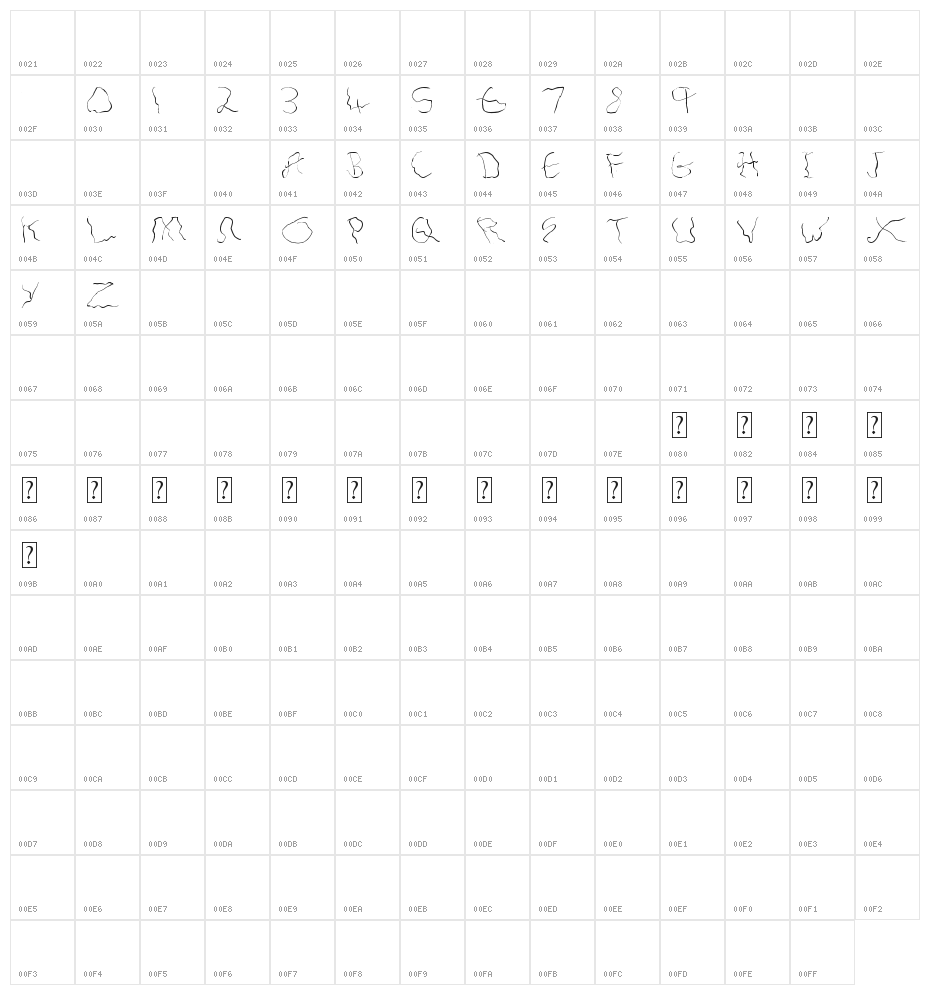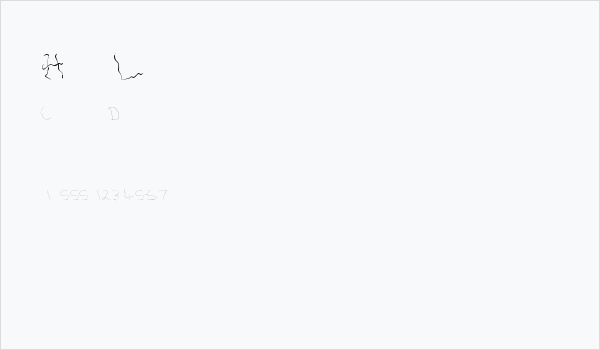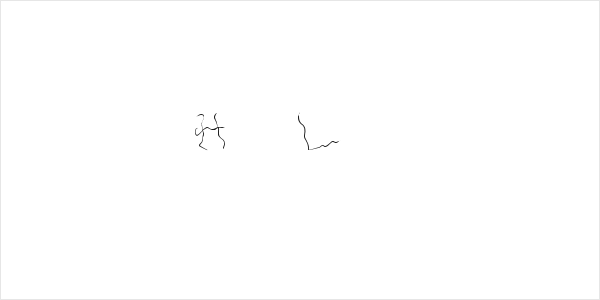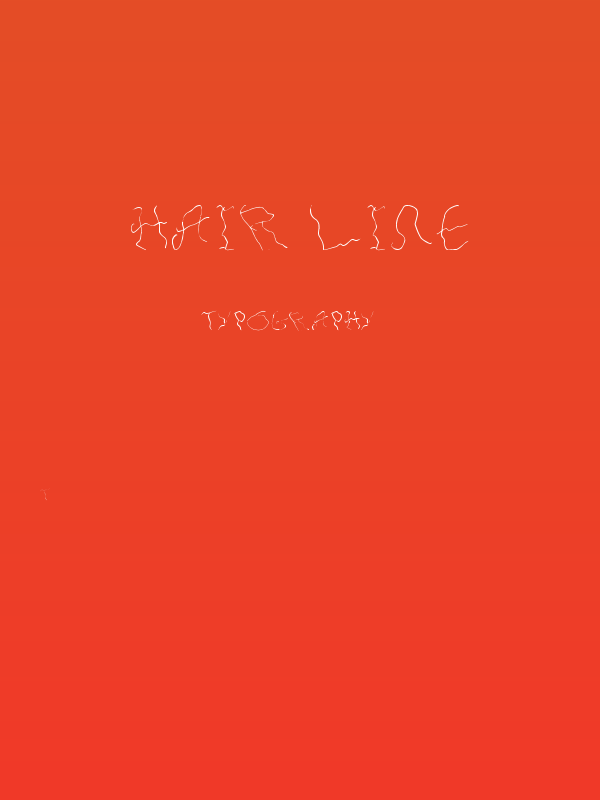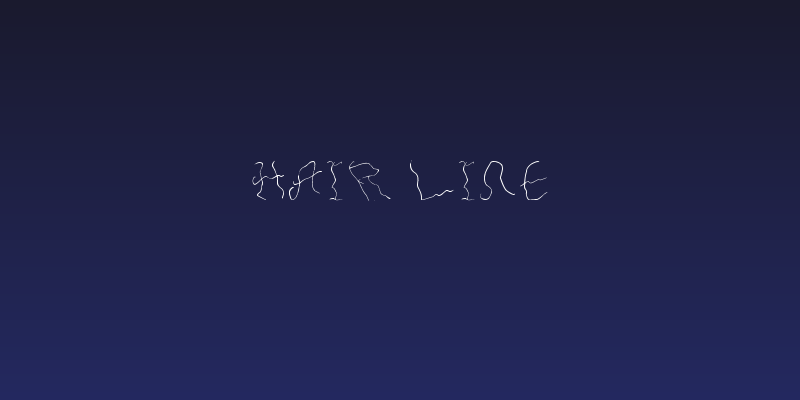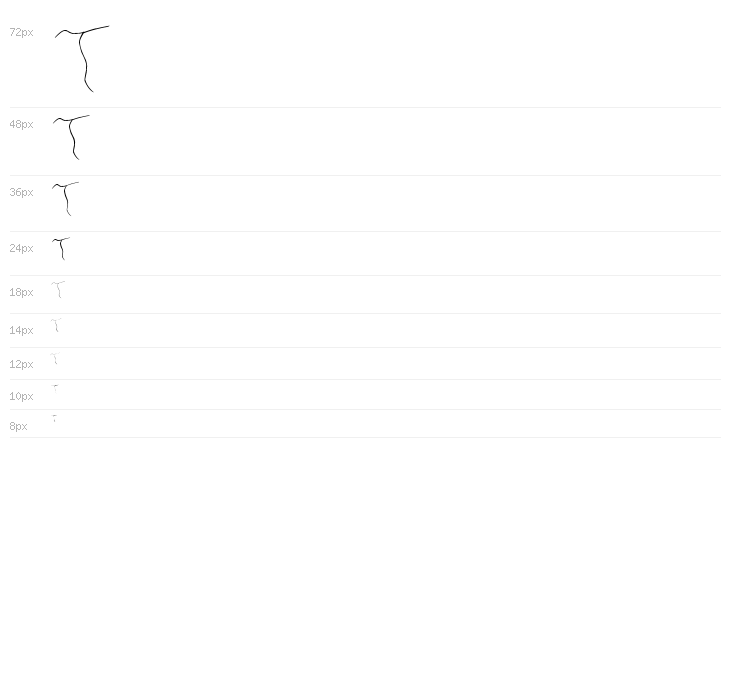
Hair Line Font
HAIR-LINE Groß
HAIR-LINE Kleinbuchstaben
HAIR-LINE Anderer Schreiben
| Anwendungsfall | Logos, Headlines, Artistic projects |
| Vorgeschlagene Projekte | Ideal for artistic projects, children's books, creative branding, and whimsical invitations. |